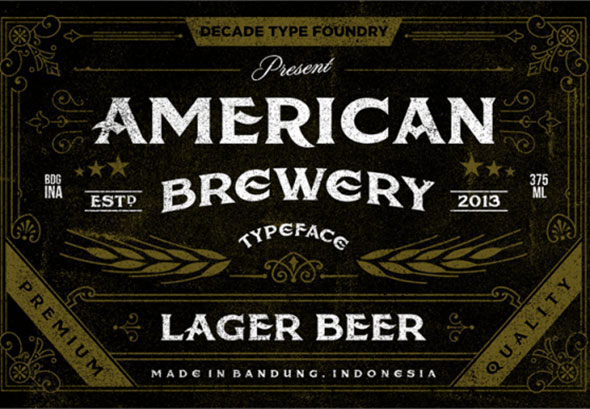
デザインを彩ってくれる無料のタトゥーフォントサンプル24選
タトゥーフォントというのはデザインの中ではメジャーなジャンルではなく、どちらかというとニッチ指向なものです。しかし、実際は多様な使い方ができますし、使い方を心得ればロゴからウェブデザインなど色々なデザインに活用できます。
本当にベストなタトゥーフォントだけを厳選しました。プロジェクトに使用可能なタトゥーの活字体はネット上に何百もあり、無料でダウンロードすることができるのですが、クオリティが高くて美しいものはほんの一握りなのです。
以下のリストには、サンセリフ体のもの、小文字、大文字、その他いろいろなサイズのものがあります。組み合わせて使うことができるので、新聞のヘッドラインや雑誌やポスター、プレゼン資料やロゴにも活用できます。それぞれの活字体はひとつか、複数のフォントで使用可能です。たとえば、標準サイズやライトサイズ、太字、イタリックなどです。同じフォントでいくつかのバージョンがあるということです。なので、シチュエーションが違っても同じフォントを使うことができます。
この無料タトゥーフォントはユニークなデザインなので、アートワークで使えば目立ちますし、印刷物にもデジタル表示にも適しています。
American Brewery Rough
American Brewery Roughは、ヴィンテージ風のポスターやロゴにぴったりです。あらゆる創作プロジェクトに使えるので、コレクションしておくと役立つはずです。
Angel Tears
The Angel Tearsというこのフォントは、ネット上で見つけられるフォントの中でも最高のものです。特に大文字のレタリングがキマっています。ずば抜けたデザイン性があるので、色々なプロジェクトにぴったりです。
Angilla Tattoo
Angilla Tattooは、個人使用は無料ですがリンク先のプレミアムバージョンもチェックしてみて下さい。インク風のものが好きな人にはたまらないはずです!ダウンロードして、今取りかかっているプロジェクトに使用してみてはいかがでしょう。
Antlers
色々なデザインに合う、ユニークな活字体です。Antlers は、他にもタトゥーに着想を得たフォントを作っています。これは個人的な使用のみ可能です。
Blessed Day
Blessed Dayは、個人使用のみ可能なフォントです。手書きのように見えるタトゥーフォントになっています。色々なクリエイティブな使い方ができそうですが、ポスターにも最適ですね。
Brother Tattoo
Brother Tattooのようなフォントを探していた人もいるのでは? レタリングも素晴らしいですが、プレビュー画像はどう使えばいいかの良いサンプルとなっています。
Canterbury
クリエイティブなデザインのフォントです。Canterburyには、何かテーマを持ったポスターやロゴなどを作るのにぴったりのタトゥーフォントがあります。
Delinquente
Delinquenteのようなフォントがあなたにはぴったりかも知れません。プレビュー画像を見てもピンとこなければ、もっとディテールを細かくみてひとつひとつの文字がどんなに素敵なデザインか見てみてください。リンク先でダウンロードして、自分のデザインの中で使ってみましょう。
Feathergraphy
次回のデザインで使いたくなるような美しいフォントです。以前のものを気にいっていたなら、今回のもおすすめです。Feathergraphy は、無料サンプルコレクションに追加すべきものです。
Ink In The Meat
Ink In the Meatは、無料サンプルの宝庫にキープしておくべきクールなフォントです。簡単にダウンロードして、次のプロジェクトに使うことができます。このクリエイティブなセリフタトゥーフォントが、探し求めていたものかどうかよくチェックしてみてください。
inuTattoo
タイポグラフィーはデザインの中でも重要なので、カスタムフォントを加えることによって出来が全然違ってきます!それぞれの文字のスケッチが組み合わされたこのタトゥーフォントは、イマジネーションを刺激してくれます。
Los Angelesは、これまで紹介してきたような丸っこくて手書きのような装飾華美なものとは違います。直線的なレタリングなので、ロゴなどのプロジェクトとうまく馴染みます。
Mardian
Mardianは、今取りかかっているプロジェクトにぴったりかも知れません。このクールなフォントを個人的なプロジェクトで使ってみてください。このフォントは使いやすく、まさに必要としていたものかも知れません!
Original Gangsta
Original Gangstaのフォントには興味を引かれるかもしれません。インク風が好きな人にはぴったりですし、コレクションに加えておくと役立ちます。
Prison Tattoo
もしかしたら、prison tattooのようなフォントを探し求めていたのではないでしょうか?テキストを使うプログラムにはぴったりです。
Reditum
Reditumは、ポスターやウェブデザインで使う大きなタイポグラフィーのようなクリエイティブなプロジェクトにぴったりなフォントです。これは、ポスターなどのクリエイティブなプロジェクトにタトゥーフォントがよく馴染むいい例ですね。
Serval
Servalは、ユニークなレタリングのタトゥーフォントです。個人的なプロジェクトに使うことを検討してみてください。もし気に入ったら、商用に使えるバージョンも用意されています。
Ananda Namaste
ネパール、サンスクリットの書体からインスピレーションを得たこのフォントはコレクションしておくと役立ちます。このユニークなタトゥーフォントを、個人的なプロジェクトでどんな風に使えるか考えてみましょう。
Teitheas
Teitheas も、インク風が好きな人にはたまらないフォントです。それぞれの文字が良くデザインされていることを見てみて、クリエイティブなプロジェクトで使ってみましょう。
Hello Sailor
Hello Sailorは、コレクションに加えておきたい細身のフォントです。特にポスターなどのクリエイティブなプロジェクトにぴったりです。
Tattoo Shop
Tattoo Shopは、ヴィンテージ風のポスターを作るならぴったりのフォントです!これは無料サンプルのコレクションに加えておきましょう。
True Love
このフォントにはレギュラーと太字バージョンがあるのですが、どちらも素晴らしいです。便利に使えて、プロジェクトの見栄えを良くしてくれます。
CM Tattoo Dragon
CM Tattoo Dragonは、インク風が好きな人にはぴったりのクールなフォントです。クリエイティブなプロジェクトにも、ウェブデザインにもぴったりです。
Death in the Shadow
Death in the Shadowは、紹介するのは最後になりましたが同じようにクールで便利に使えて、目立つのでプロジェクトの見栄えをよくしてくれるフォントです。これがタトゥーにインスピレーションされたデザインでどれほど使いやすいか考えてみましょう。